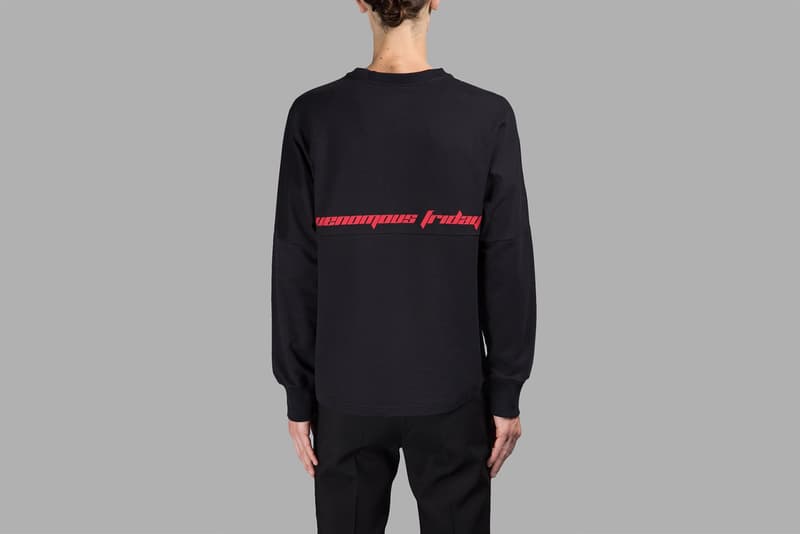
Kanye West 与 Raf Simons 共同定义全新时尚字体
新一轮的「字体热」蓄势待发。
Kanye West 今年通过「Pablo」掀起了一场全球化的「Old English」字体热,而这种哥特风格也即将被另一种名为「Planet Kosmos」字体所承接。这种字体最初由 Mads Rydahl 于 1996 年为夜店所创作,而早前更已现身于 Kanye West 与 adidas 的全新 Calabasas 企划,以及 Raf Simons 2017 春夏系列的设计中。据悉,Kanye West 与 Raf Simons 已相继从 Rydahl 获得「Planet Kosmos」的商业用途授权,但并没有透露具体的利益回报。「Old English」与「Planet Kosmos」这两种字体,你又更偏爱哪个呢?